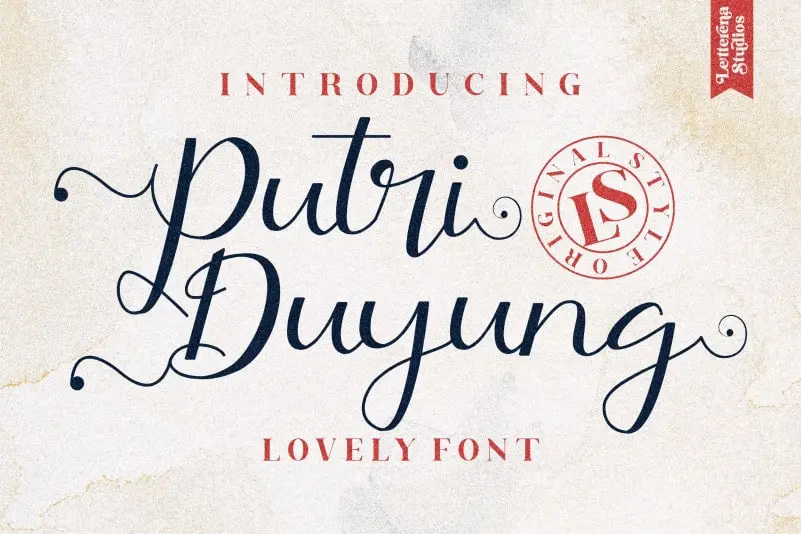
Putri Duyung Calligraphy Font – Download Grátis
A Putri Duyung Calligraphy Font é uma elegante letra escrita a mão que vai fazer sua criação sobressair. Essencialmente fluída e feita para quem deseja um estilo distintivo e eterno, esta fonte será o seu complemento perfeito para projetos favoritos. Com acesso fácil a todos os sinais e desenhos vibrantes graças ao PUA encodado, você cairá apaixonadamente no seu formato único. Experimente sua versatilidade em designs inovadores; ela é mais que uma escolha de fonte, é um recurso para tornar seus projetos ainda mais especializados. Que tal adicionar um toque autêntico e diferenciado a suas criações? Descubra a beleza de Putri Duyung Calligraphy Font.